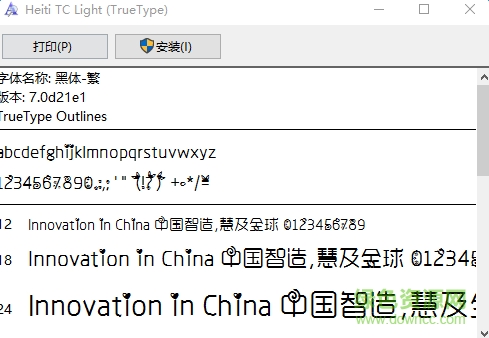
卷卷愛(ài)紅唇是一款很有個(gè)性的電腦藝術(shù)字體,也正是因?yàn)檫@款字體比較有特色,所以很多年輕人都喜歡用這款字體,寫(xiě)出來(lái)的字是極美的,歡迎大家來(lái)綠色資源網(wǎng)下載。
卷卷愛(ài)紅唇字體是真的很不錯(cuò)哦,小編已經(jīng)幫大家試用過(guò)了,寫(xiě)出來(lái)的字效果很不錯(cuò),可以用于很多方面,大家可以來(lái)綠色資源網(wǎng)下載使用。